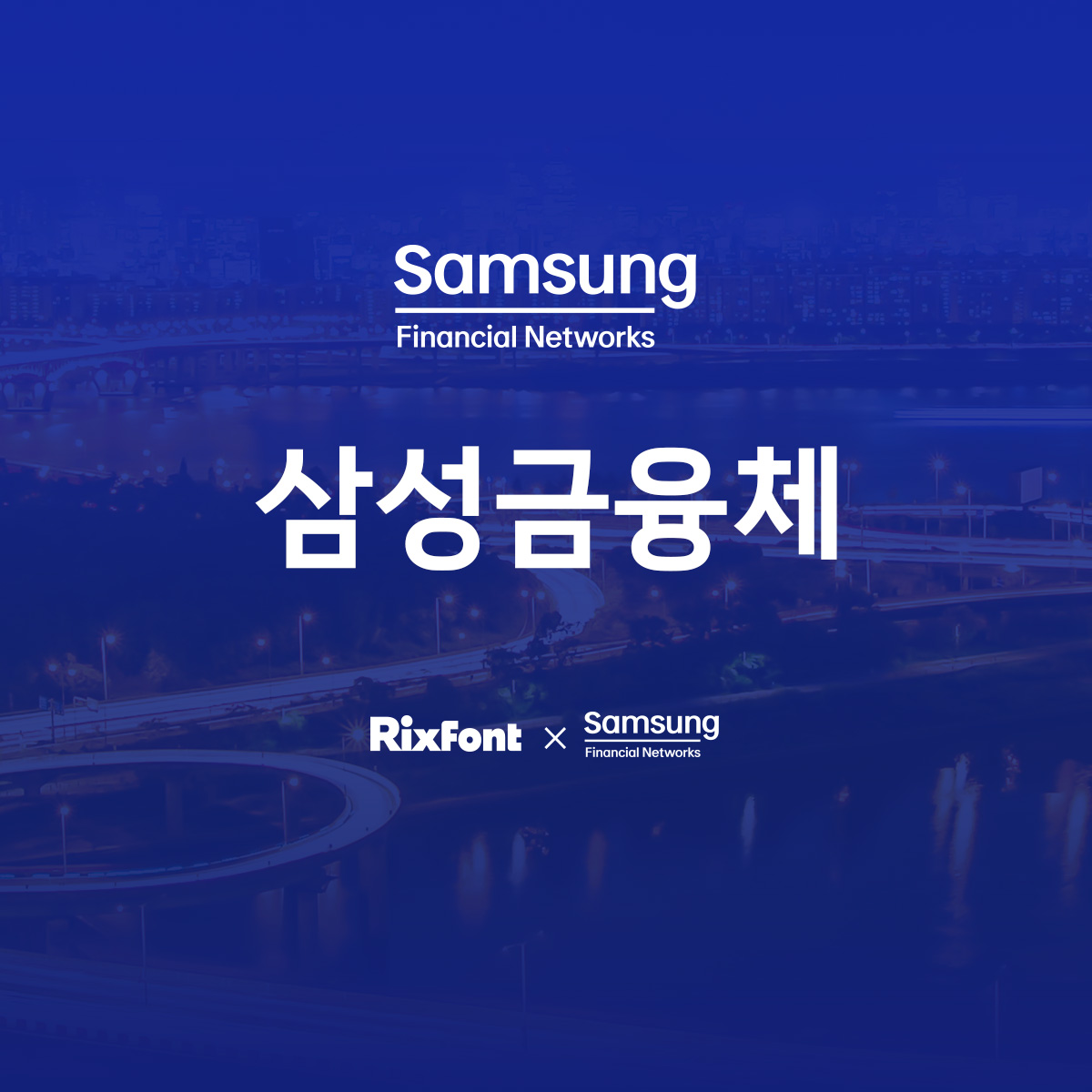
젊고 유연한 이미지로 새롭게 시작하는 삼성금융네트웍스의 전용서체, 삼성금융체입니다.
삼성금융체의 핵심 키워드는 젊음, 유연함입니다. 골격은 경쾌하고 산뜻한 인상을 줄 수 있도록 탈네모틀 구조로 설계했고, 금융사의 정체성을 담기 위해 지폐에 쓰이는 '0'의 형태를 차용했습니다.
그리고, 삼성의 핵심 자소인 'ㅅ'에 아이덴티티를 담아 'ㅅ+ㅏ'와 'ㅅ+ㅓ'의 결합에서 'ㅅ' 주변의 공감에 따라 자연스럽게 변주되는 방식을 디자인에 적용했습니다. 이는 고딕계열 서체에서는 거의 처음 시도되는 방식입니다.